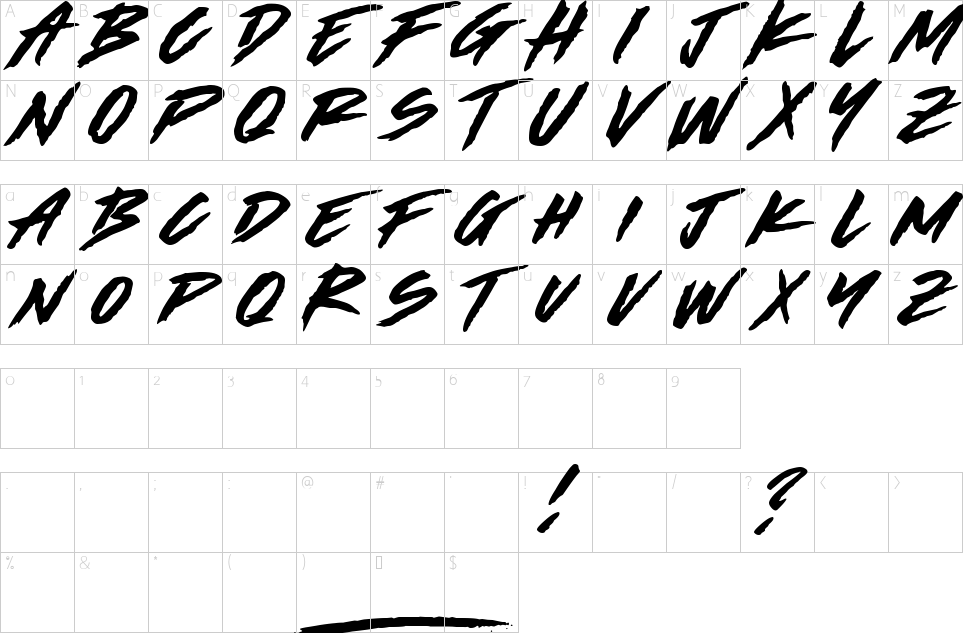
A fonte ‘Made By Bears Font | 1001 Free Fonts’ é um recurso visual inovador para designers gráficos e amadores que procuram uma fonte elegante e versátil. Desenvolvida pelo The Branded Quotes, essa font é uma ótima opção para aqueles que buscam uma maneira criativa de destacar seus projetos. Disponível tanto para Windows quanto para Mac, a ‘Made By Bears Font’ é uma ferramenta versátil para criar títulos chamativos, headlines e textos mais profundos, trazendo um toque único e moderno a qualquer projeto. Com seu design refinado e arquitetura fácil de usar, é fácil encontrar a fonte perfeita para seu próximo design. Download da fonte gratuita e com estilo ‘Made By Bears’, e comece a dar um toque especial à sua arte digitais.